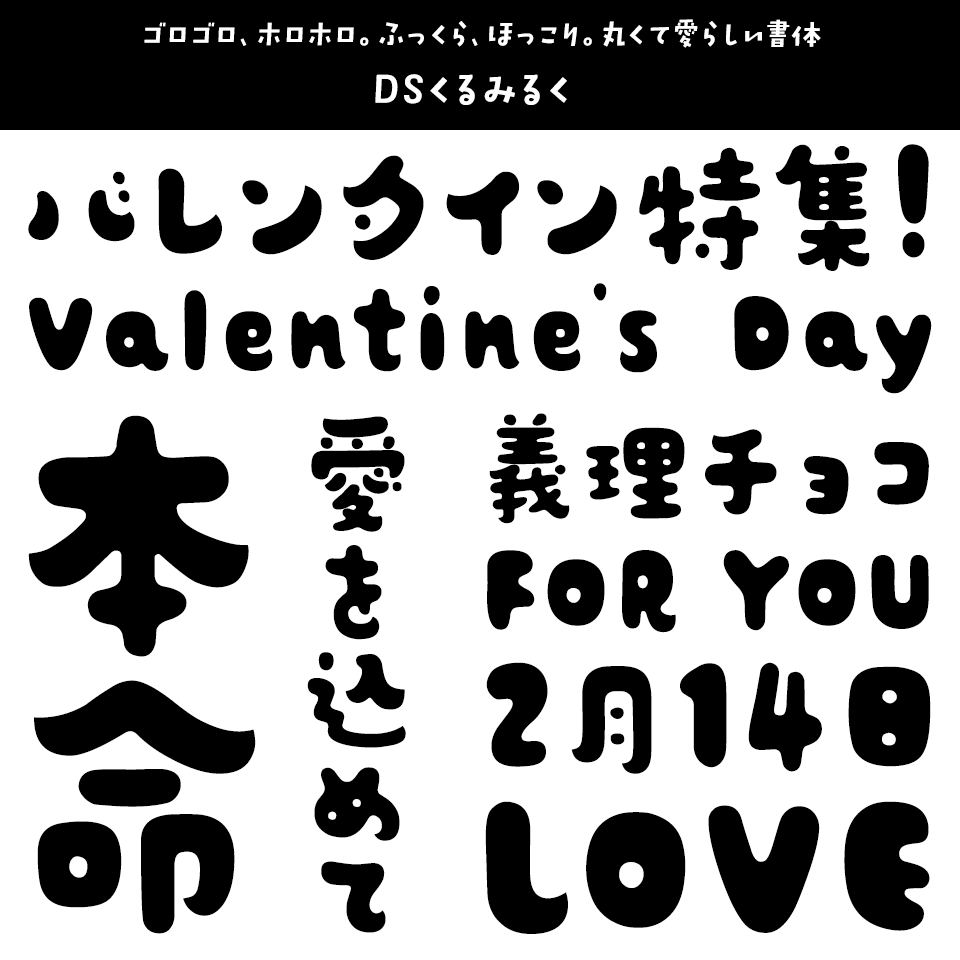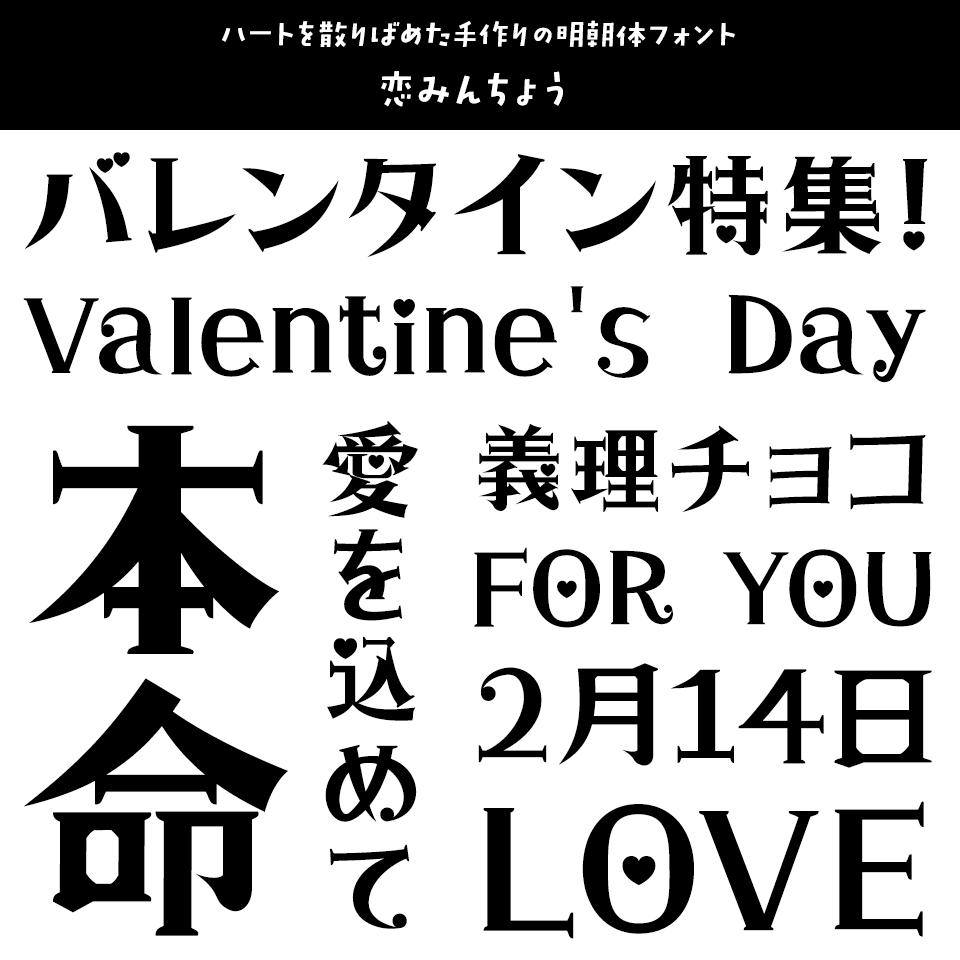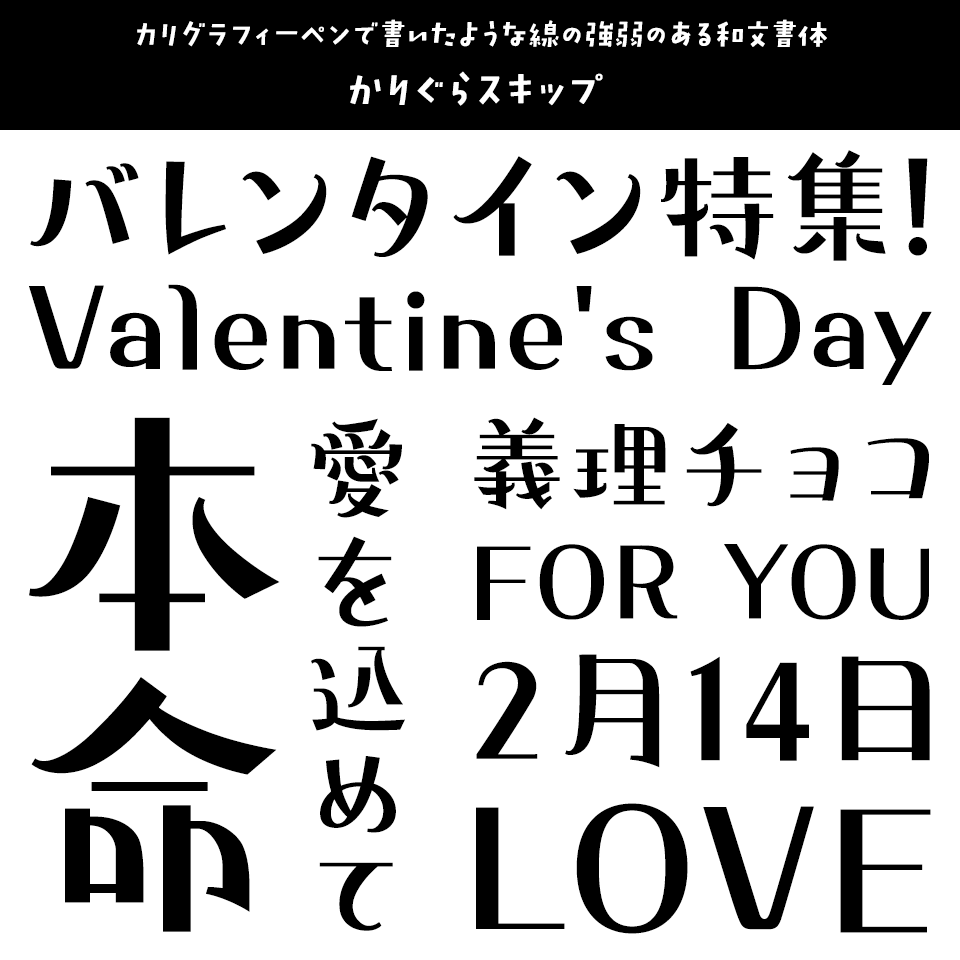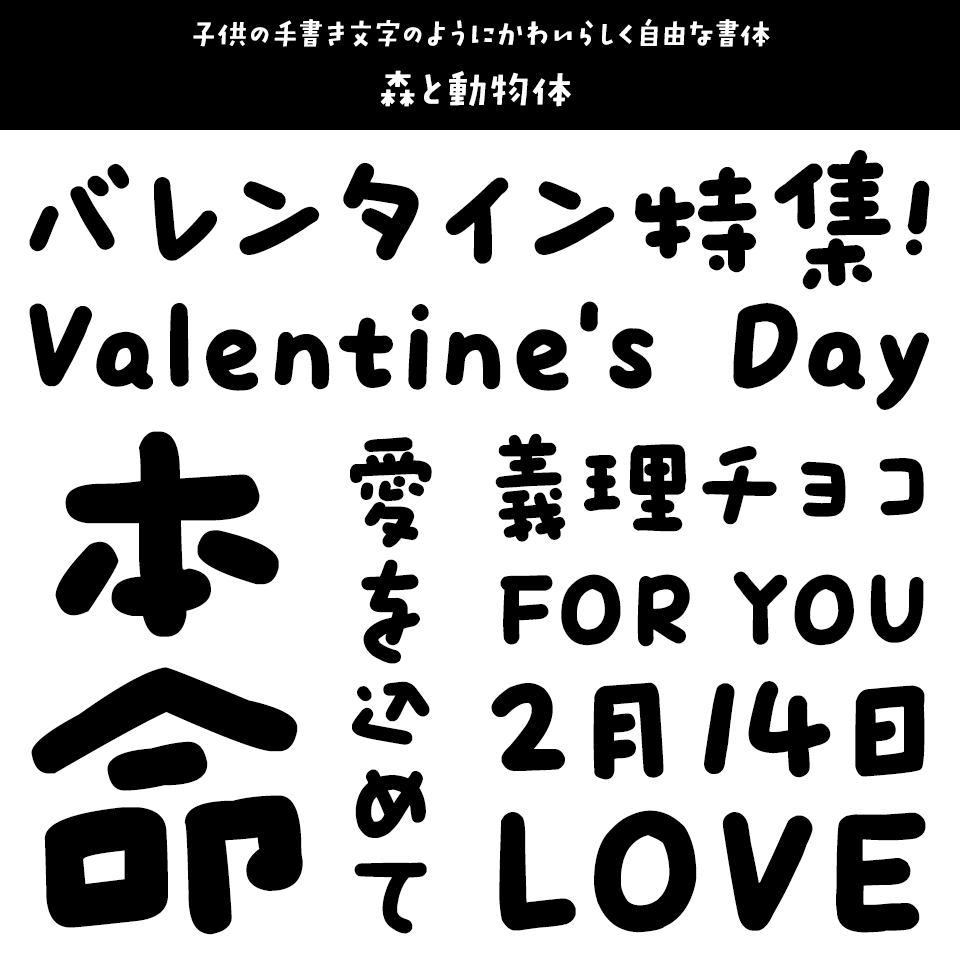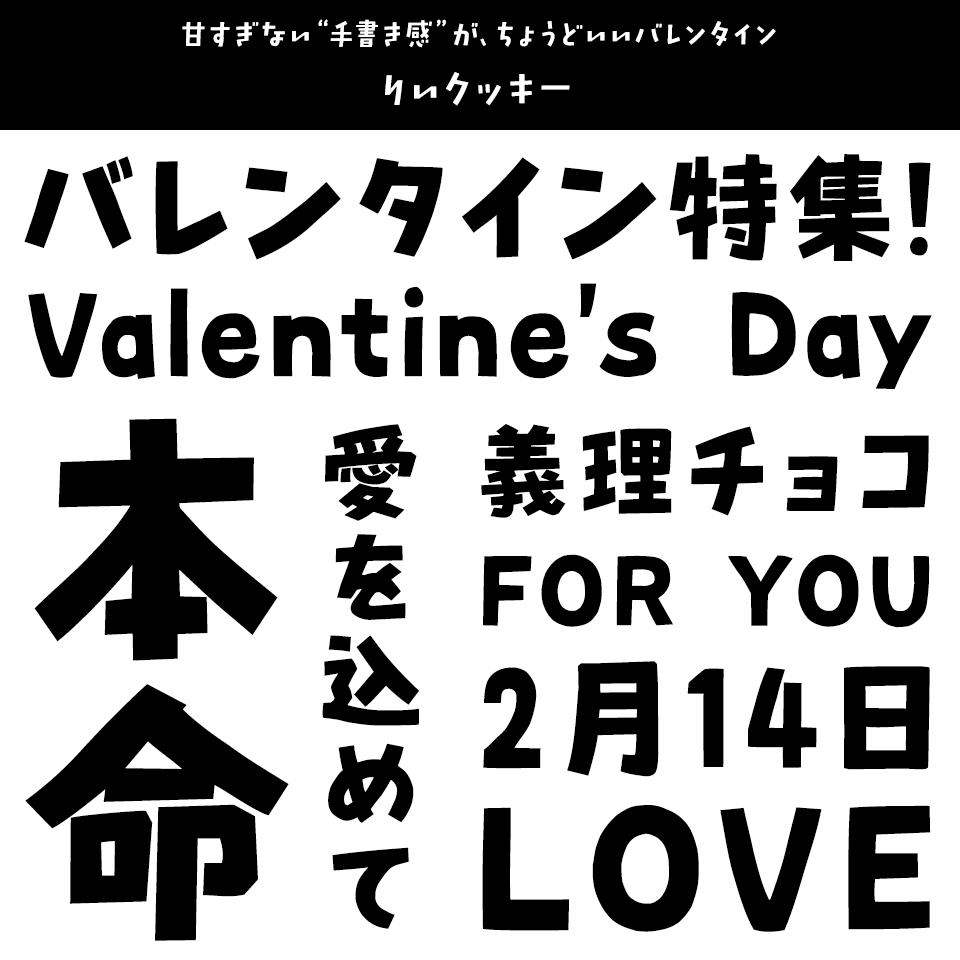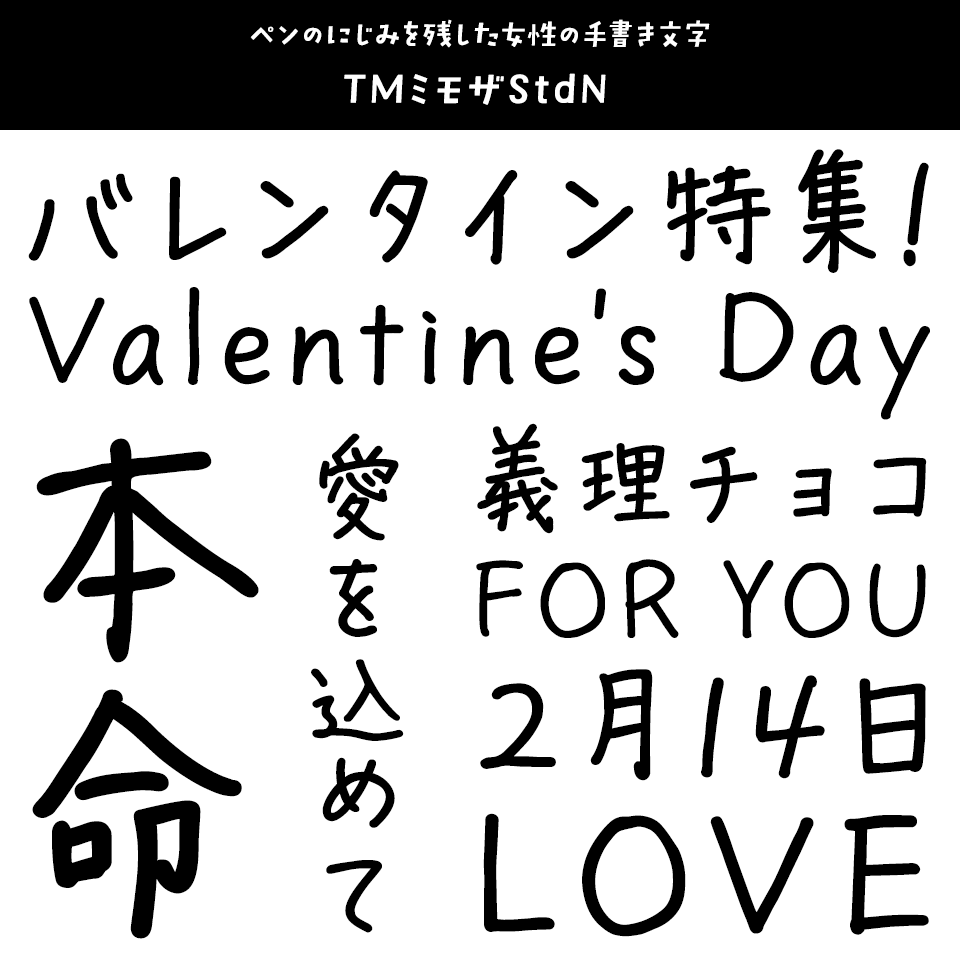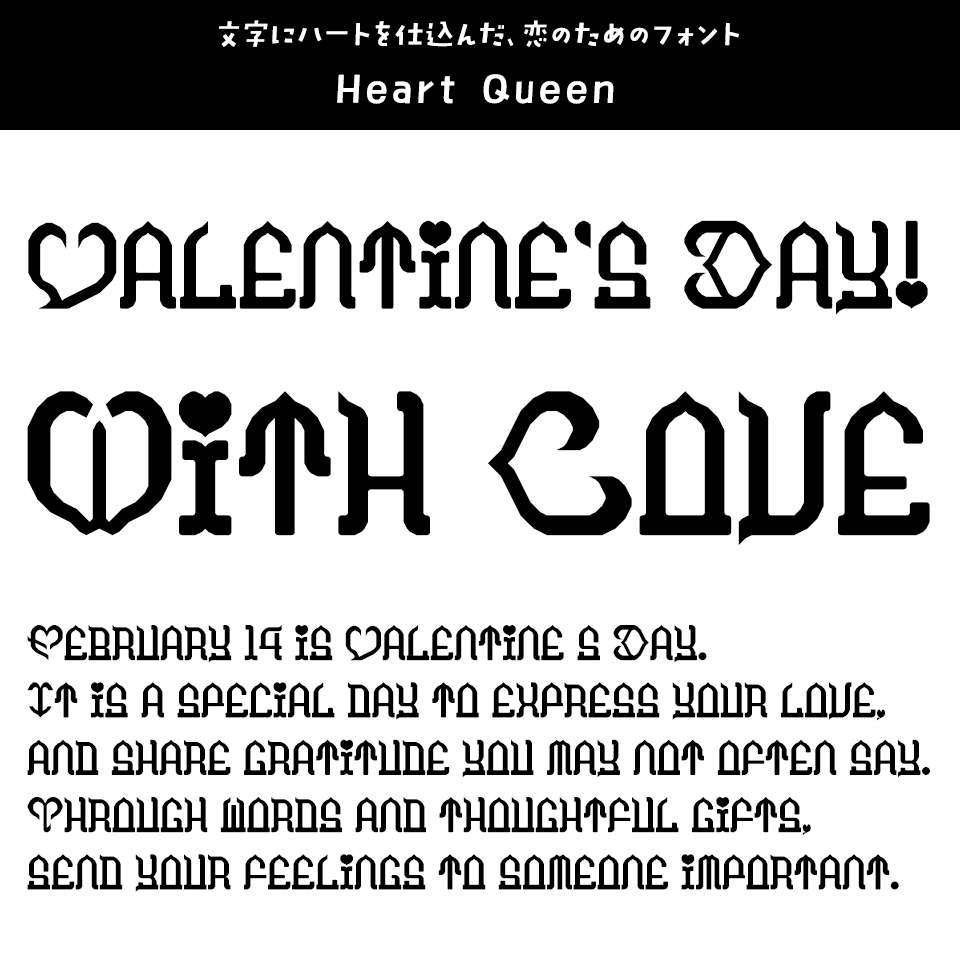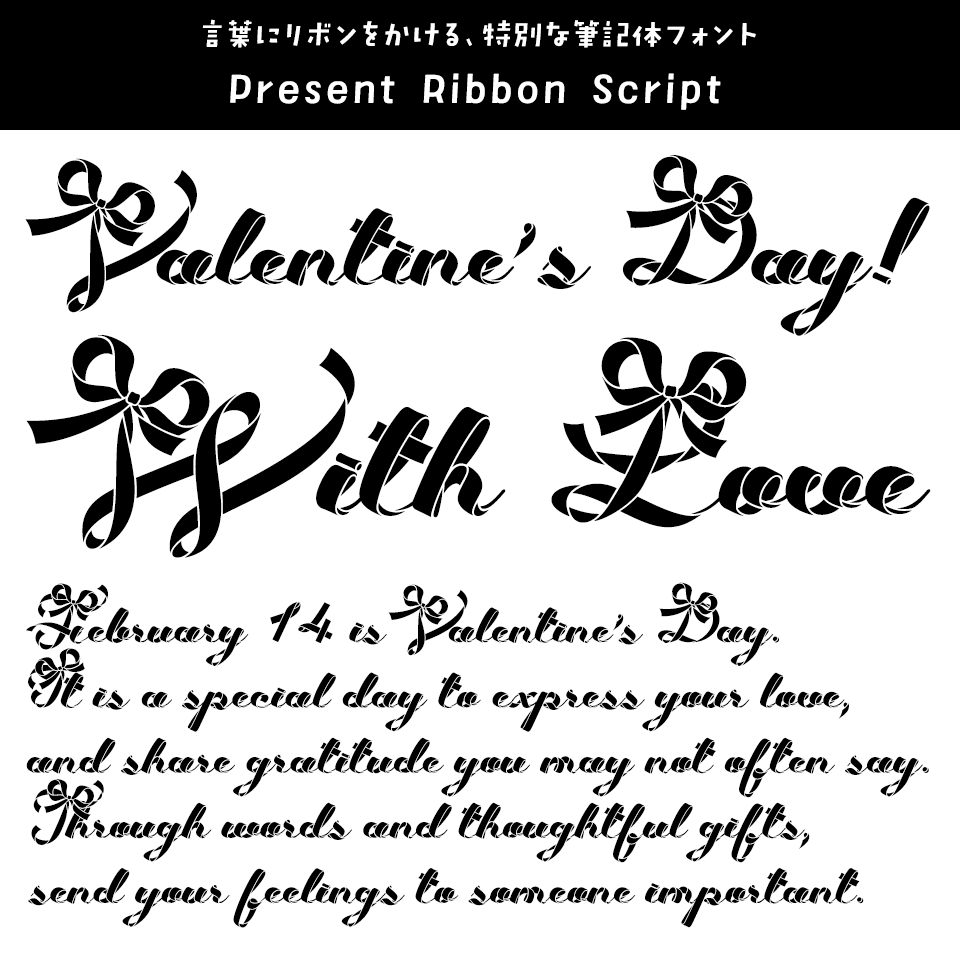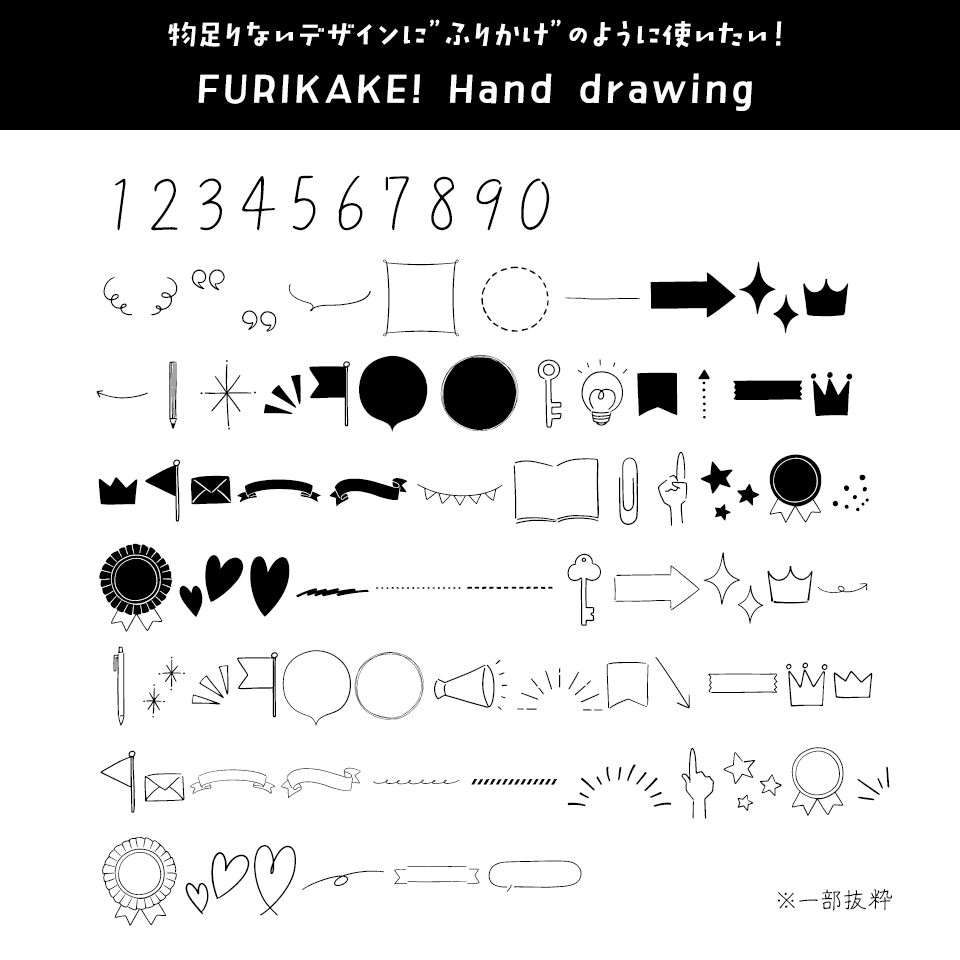
「バレンタイン」に合うフォント:特化型 目的別フォントガイド #180
今回は「バレンタイン」に合うフォント。日々フォントのことばかり考えている当店スタッフが直感的に選んだフォントをご紹介します。
「バレンタイン」に合うフォントをスタッフが選びました
「バレンタイン」に合うフォント DSくるみるく
ゴロゴロ、ホロホロ。ふっくら、ほっこり。丸くて愛らしい書体
「バレンタイン」に合うフォント DSくるみるく
手づくりクッキーやパンを思わせる、味わいのあるデザイン書体。チョコがとろりと溶け出しそうなやわらかな形と、どこか懐かしい雰囲気が魅力です。可愛いお菓子に、この書体でメッセージを添えるのもおすすめ。
「バレンタイン」に合うフォント 恋みんちょう
ハートを散りばめた手作りの明朝体フォント
「バレンタイン」に合うフォント 恋みんちょう
所々にハートが隠れている可愛らしい明朝体。バレンタインの想いやときめきをやさしく引き立てます。女性らしいカードやメッセージなど、素直な気持ちを伝えたいデザインにおすすめ。
「バレンタイン」に合うフォント かりぐらスキップ
カリグラフィーペンで書いたような線の強弱のある和文書体
「バレンタイン」に合うフォント かりぐらスキップ
まるでスキップをしているような軽快なハネが特徴的な、リズム感のある書体。文字の動きが、バレンタインの楽しさやワクワク感を演出します。友チョコやカジュアルなカード、イベントPOPにおすすめ。
「バレンタイン」に合うフォント 森と動物体
子供の手書き文字のようにかわいらしく自由な書体
「バレンタイン」に合うフォント 森と動物体
森や動物を思わせる、太めの丸筆タッチが魅力の手書き風書体。楽しく自由な文字表現が、愛らしい気持ちや遊び心を盛り上げます。カードやメッセージ、ポップなどにおすすめ。
「バレンタイン」に合うフォント りいクッキー
甘すぎない“手書き感”が、ちょうどいいバレンタイン
「バレンタイン」に合うフォント りいクッキー
紙に書いた手書きの温かみをそのまま活かしたフォントで、メッセージに照れくささのない親しみを添えてくれます。友チョコ・義理チョコ・推しチョコなど、カジュアルで楽しいバレンタインシーンにぴったりなフォントです。
「バレンタイン」に合うフォント 左利きの彼女
細くて少し小さい繊細な印象の手書きフォント
「バレンタイン」に合うフォント 左利きの彼女
左利きの作者が丁寧に書いた手書き文字をフォントにしました。日常で使う文字数をカバーしているので手紙やメッセージカードなど女性らしさが欲しいところで活躍するフォントです。
「バレンタイン」に合うフォント TMミモザStdN
ペンのにじみを残した女性の手書き文字
「バレンタイン」に合うフォント TMミモザStdN
自然で穏やかな手書き文字は、大人の女性らしいメッセージの演出にピッタリ!使い勝手の良い装飾素材をaiデータで収録しています。
「バレンタイン」に合うフォント Heart Queen
文字にハートを仕込んだ、恋のためのフォント
「バレンタイン」に合うフォント Heart Queen
Heart Queen は、文字の中にハートマークのシルエットを自然に溶け込ませた、遊び心と愛らしさを兼ね備えた変形フォントです。チョコレートのパッケージ、カード、SNS投稿やイベント用ビジュアルなど、“恋をテーマにしたデザイン”を一瞬で成立させたい場面 に最適です!
「バレンタイン」に合うフォント Fancy Star Script
少しレトロでポップな雰囲気の筆記体フォント
「バレンタイン」に合うフォント Fancy Star Script
くるんとした曲線が愛らしい、ポップでレトロな欧文スクリプト書体。装飾的で華やかな文字表情が、バレンタインのときめきや特別感を演出します。
「バレンタイン」に合うフォント Present Ribbon Script
言葉にリボンをかける、特別な筆記体フォント
「バレンタイン」に合うフォント Present Ribbon Script
文字がリボンのように連なり、メッセージをラッピングするように飾り付けられるのが特長です。想いを包んで、結んで、そっと渡す。そんなバレンタインのシーンにぴったりの筆記体フォントです。
「バレンタイン」に合うフォント FURIKAKE! Hand drawing
物足りないデザインに”ふりかけ”のように使いたい!
「バレンタイン」に合うフォント FURIKAKE! Hand drawing
あしらいに使える飾りを欧文フォント化。出てくるかざりは手描きで描いたものを取り込みました。可愛くなりすぎなくシンプルで使い勝手が良い装飾です。